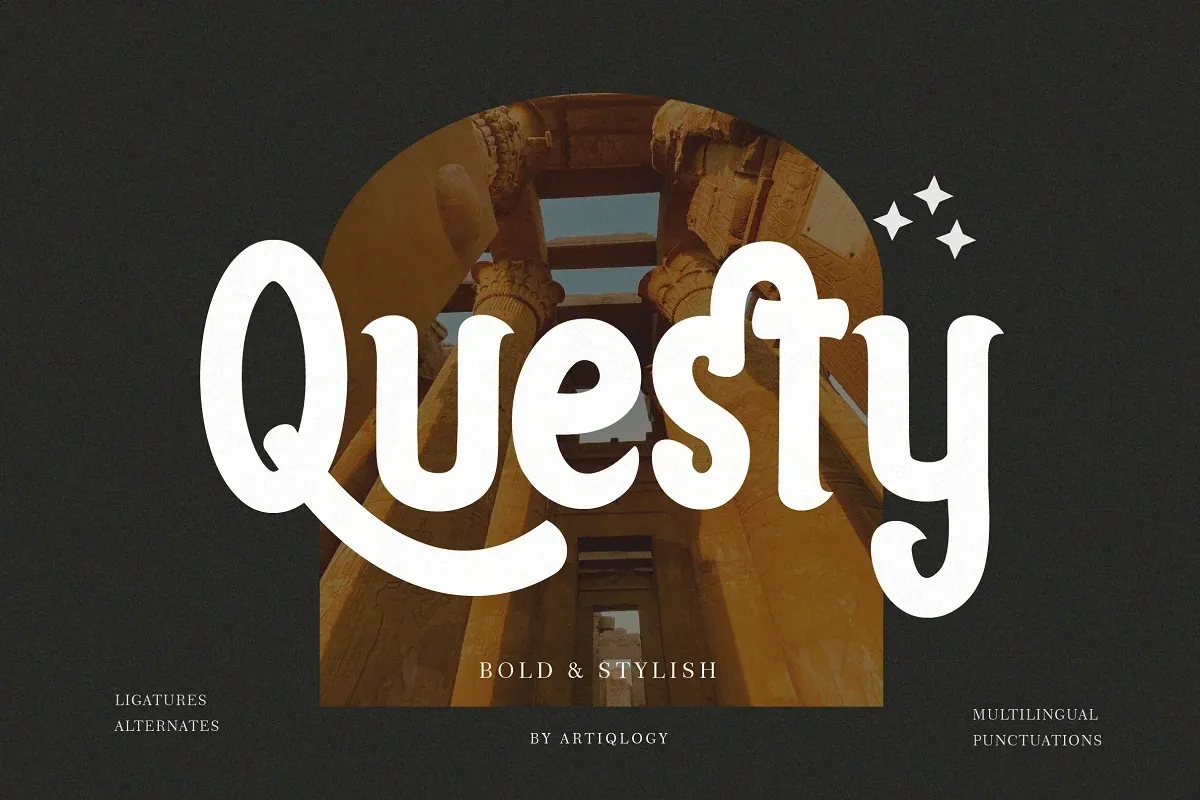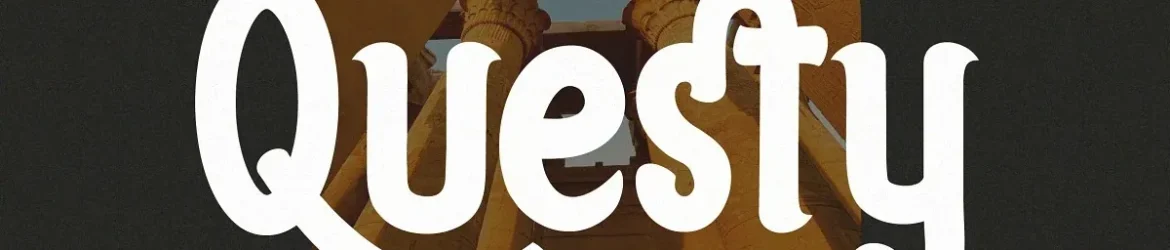
A Questy Font é uma fonte display única criada pela Artiqlogy com caracteres escritos a mão que apresentam beleza e força. Esta fonte traz um toque irresistivelmente contemporâneo aos designs, tornando-os ainda mais chamativos. Seja para criar gráficos de newsletter ou ilustrações interativas, essa fonte oferece uma expressão vibrante que destacará seu trabalho. Adicione a Questy Font a cada projeto criativo e descubra como ela transforma simples conceitos em verdadeiros elementos de design inovadores.